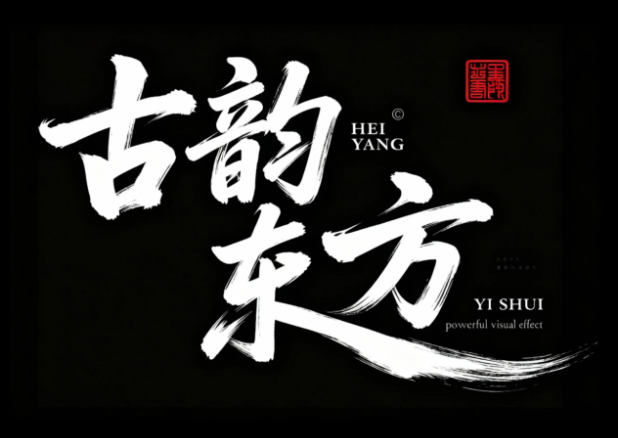
书法连笔潇洒飘逸灵动字体设计"古韵东方",草书...
书法连笔潇洒飘逸灵动字体设计"古韵东方",草书...AI字体提示词
书法水墨完整提示词可直接复制
风格定位
适合做风格探索与字形灵感延展。
适合场景
海报设计、品牌标题、电商设计、创意视觉
书法连笔潇洒飘逸灵动字体设计"古韵东方",草书字体狂野奔放,长笔画,视觉张力富有动感,笔画流畅飘逸,笔画巧妙延长变形,飞白效果,字体大小变化,错位排版。笔画流畅洒,干净背景,搭配衬线小英文"HEIYANG"排版,右边点缀红色传统印章;大师作品,电影主题字体,视觉冲击力强,字体纯白色,背景纯黑色。
可替换关键词
金属纸张肌理浮雕高对比立体阴影强笔触草书字体狂野奔放长笔画视觉张力富有动感笔画流畅飘逸